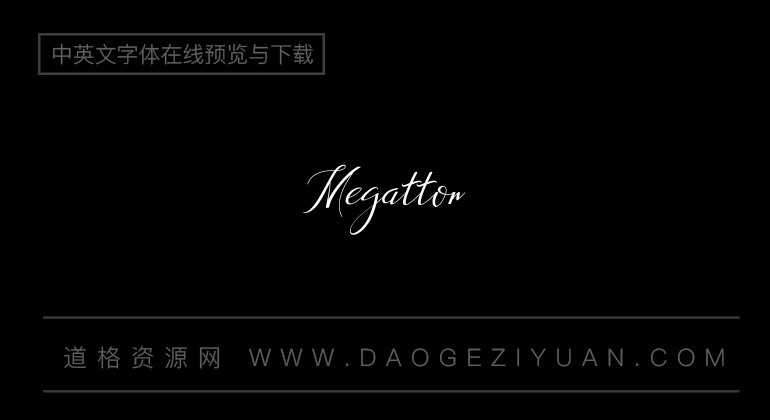
Megattor
? Megattor 字体是一款简洁、细腻、优雅的英文字体。它具有清晰的细节、深沉的线条以及明显的节奏感,能够为文档和平面设计带来更好的视觉效果。它的字形结构更加紧凑,有助于提升文档的可读性和可视性,适合用于报刊、海报、书籍、网站等多种场景。
Megattor是一款非常不错的手写艺术字体,具有很好的视觉感,适合于文化类的宣传设计、商业类品牌的广告和产品包装设计以及个性化文字排版等较多场景。